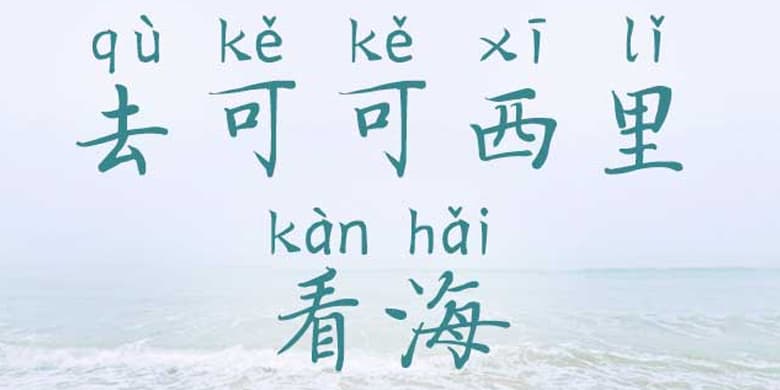
品牌:方正手迹设计师:谢龙龙发行时间:2020字库编码:大陆简体(GB2312-80)分类:常规书写·硬笔字体属性:精品字
形成灵动、清雅之风格,凝而不拙,疏而不散。随意中透出洒脱,给人一种宽博淡远的美感。结构严谨,行笔自然,阅读性极强。适用于现代诗歌、短文的排版以及文化、商业类品牌的广告语设计。